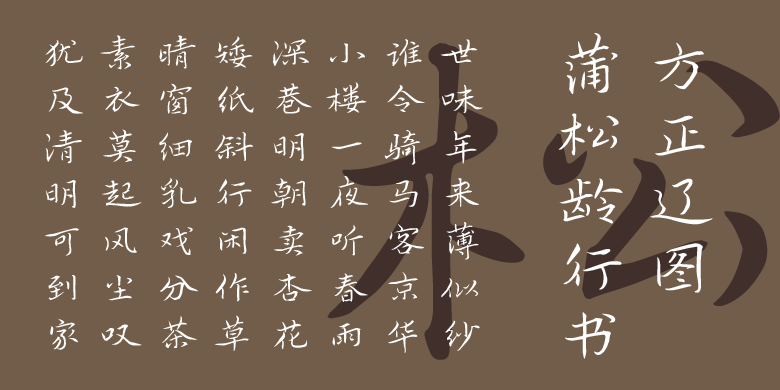
方正辽图蒲松龄行书
郭毓海
常规书写·毛笔
辽图蒲松龄行书是根据《聊斋志异》手稿设计而成。《聊斋志异》手稿字数高达20多万字,其不同篇章的字迹有差异,或工稳,或草率,或疏朗,或紧凑。在设计过程中,注重遵循古籍风貌,还原其笔法特点和间架特点,并重点关注字体排版的整体效果,在字号、字距接近原稿时,整体观感也与原稿接近。按甲方需求,在整体上令字形略作扁势,为了适应现代排版,弱化了字形大小、粗细对比,并使其排列基本整齐,但保留了诸多变化,以体现手稿独特的古拙、灵动、幽玄之美。